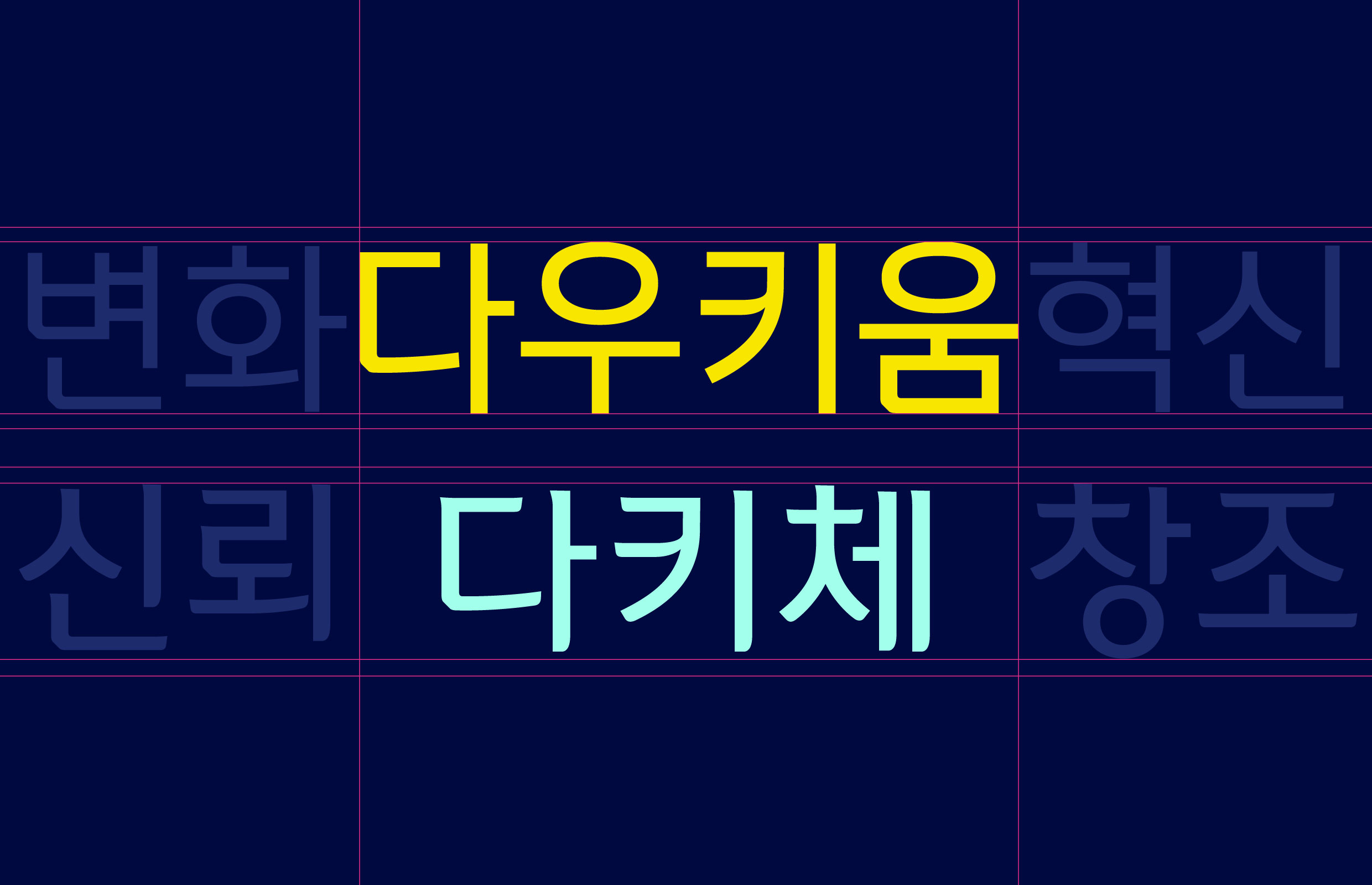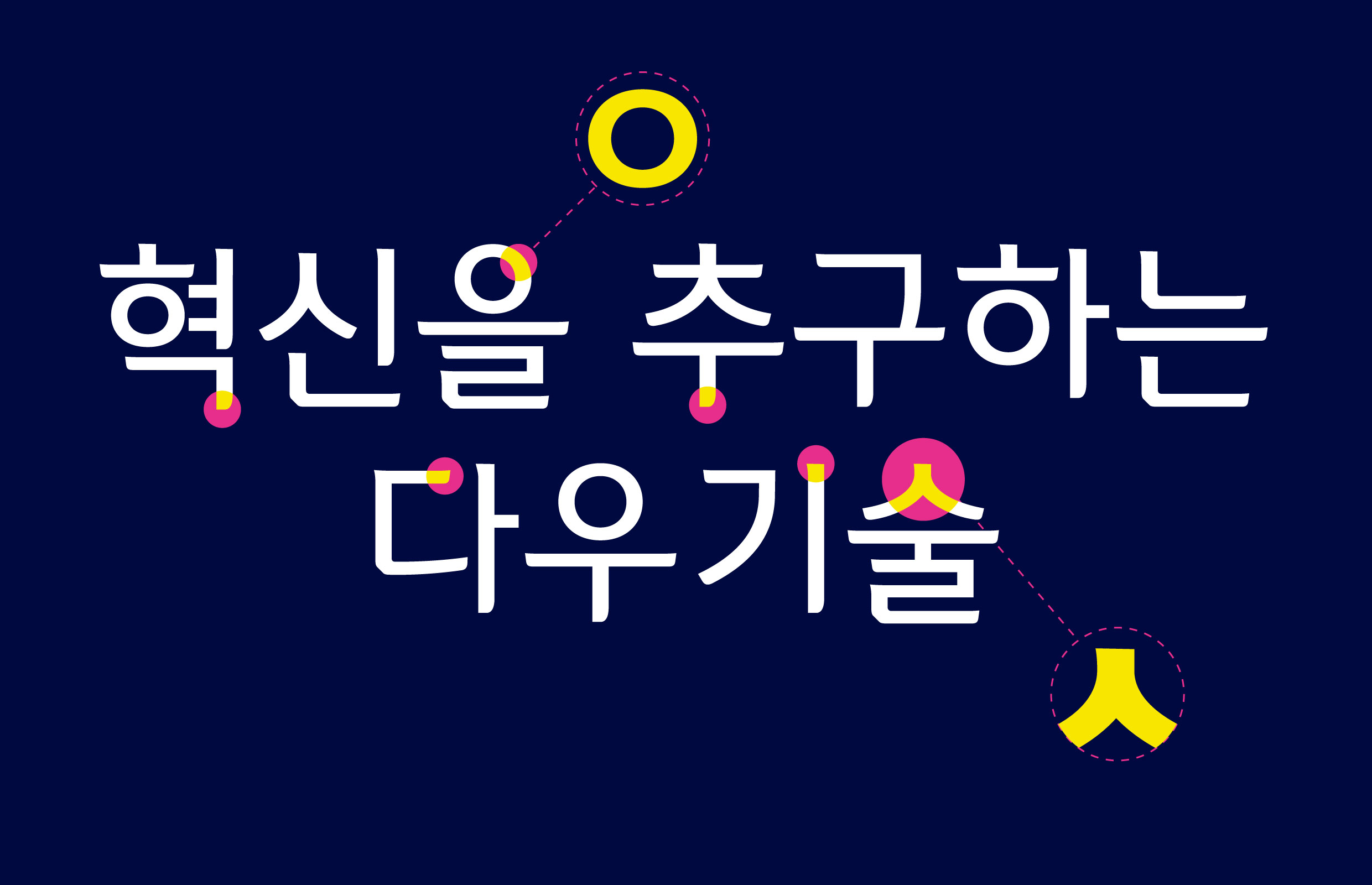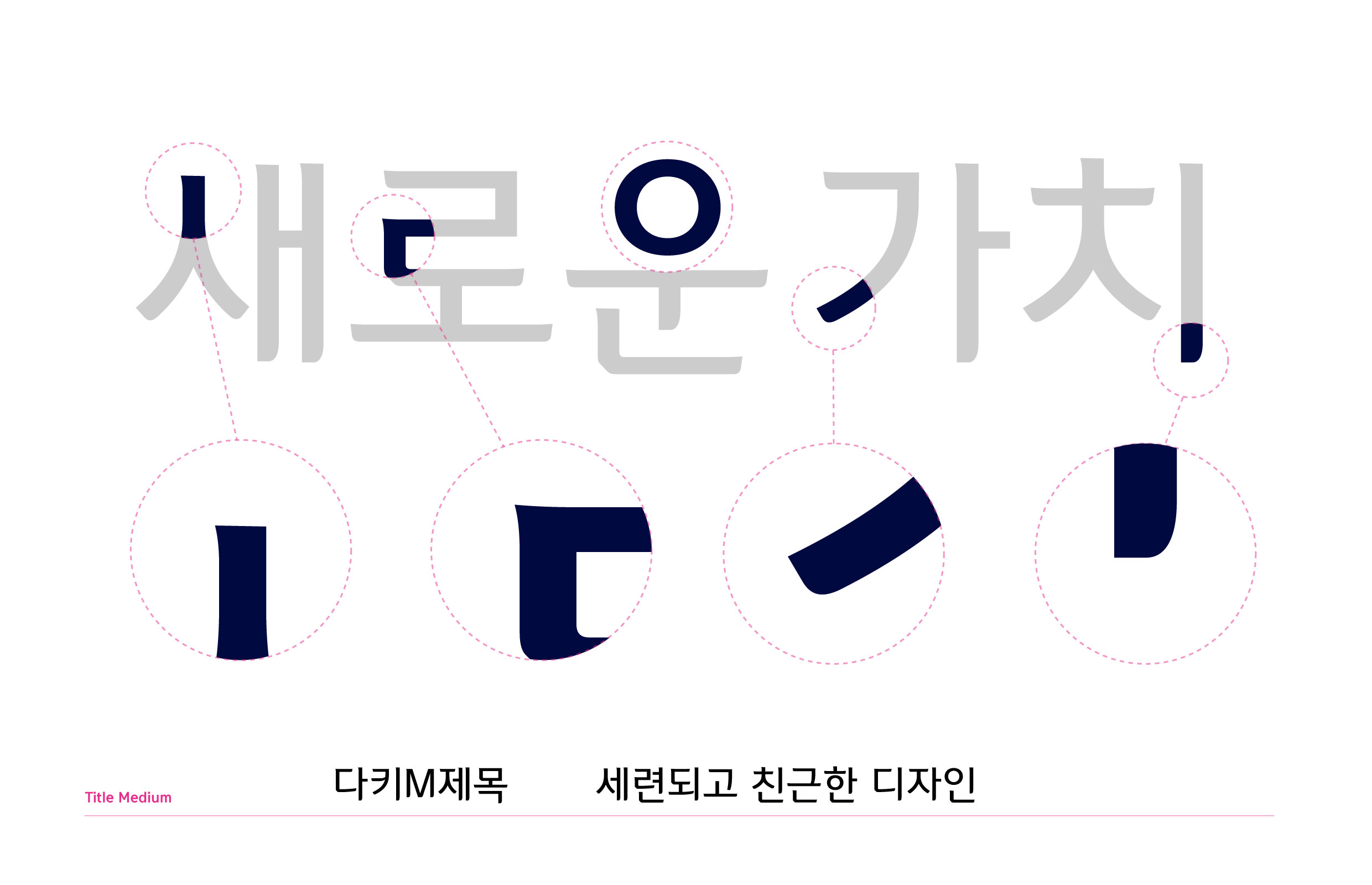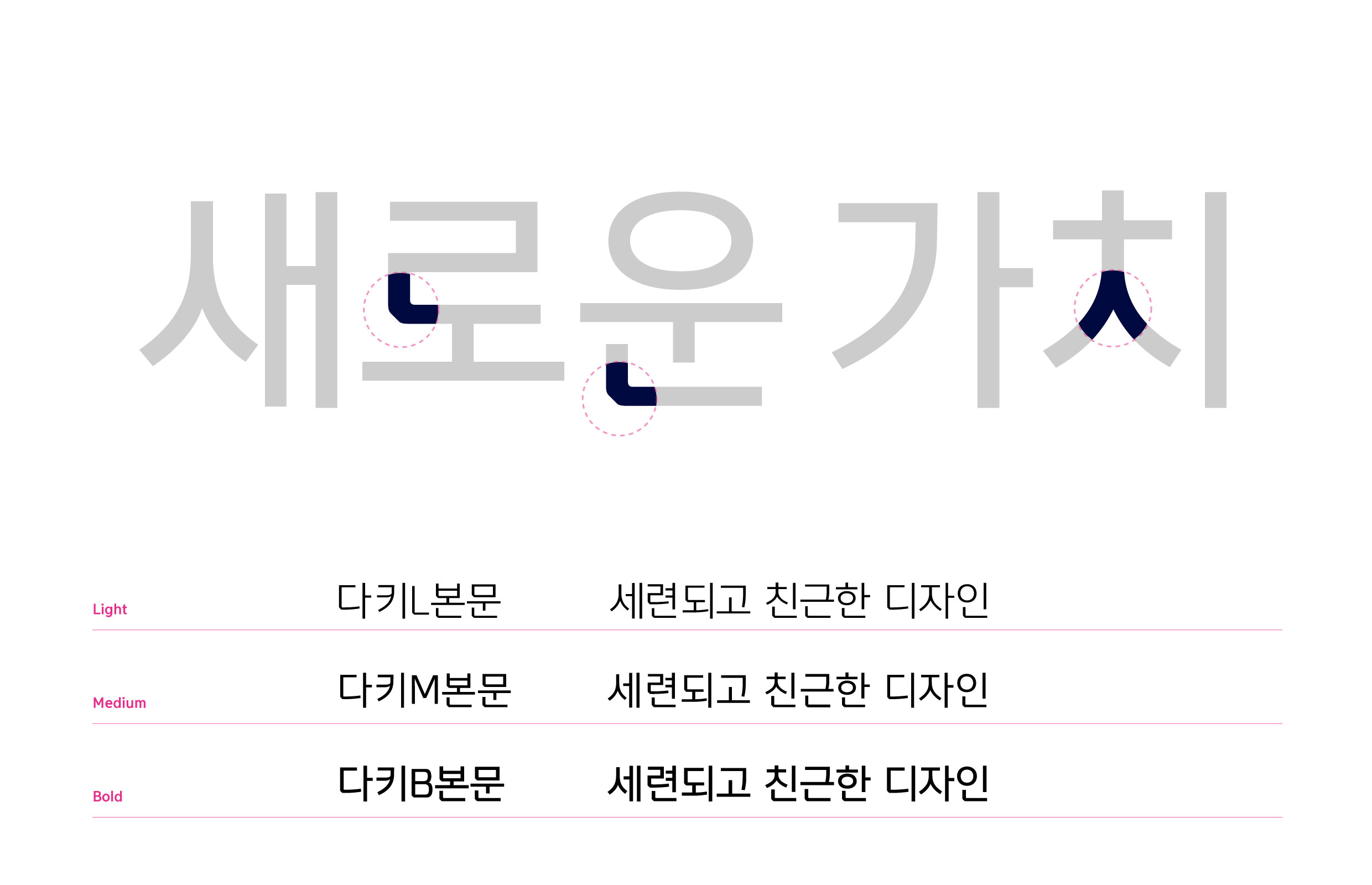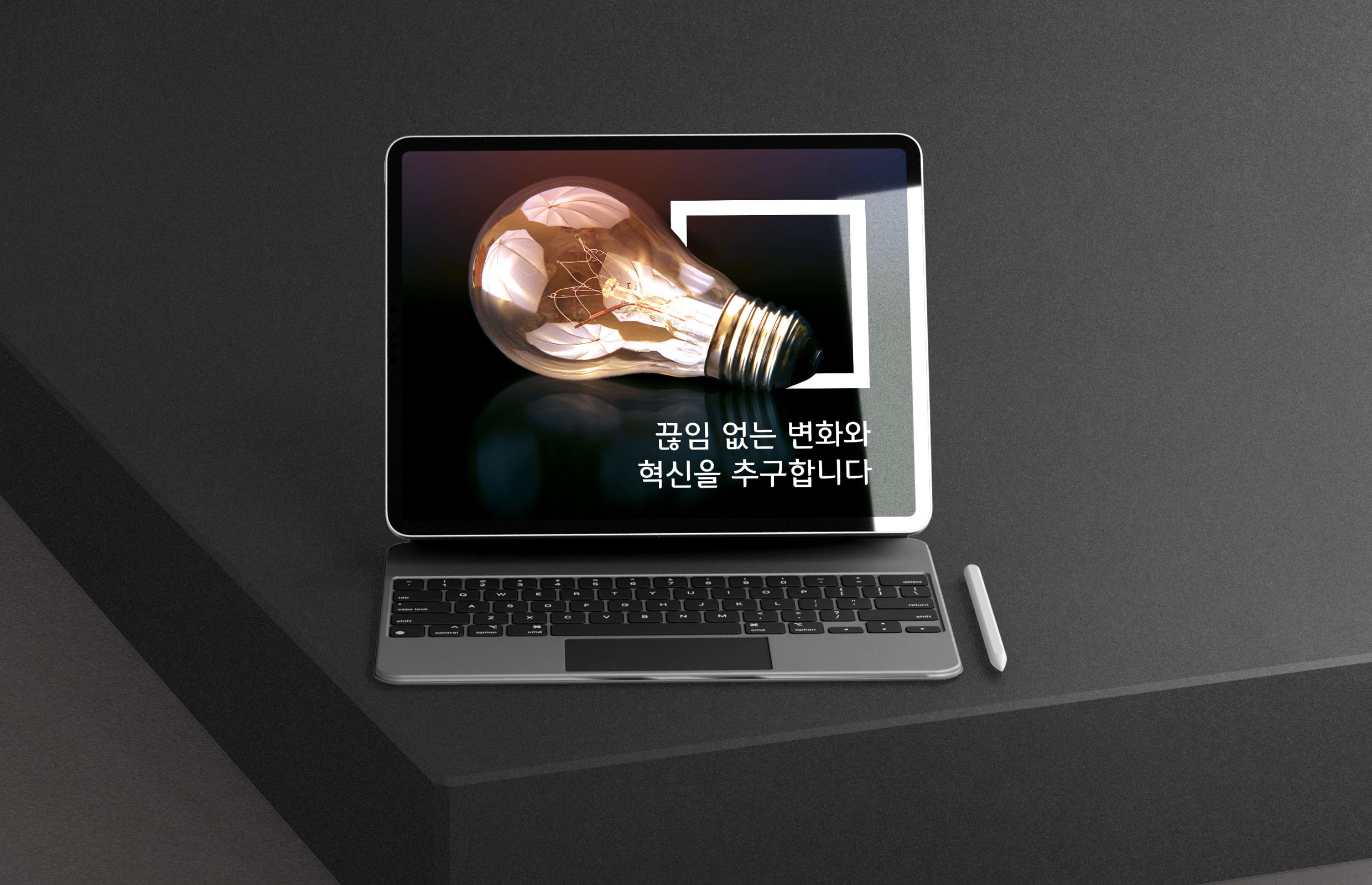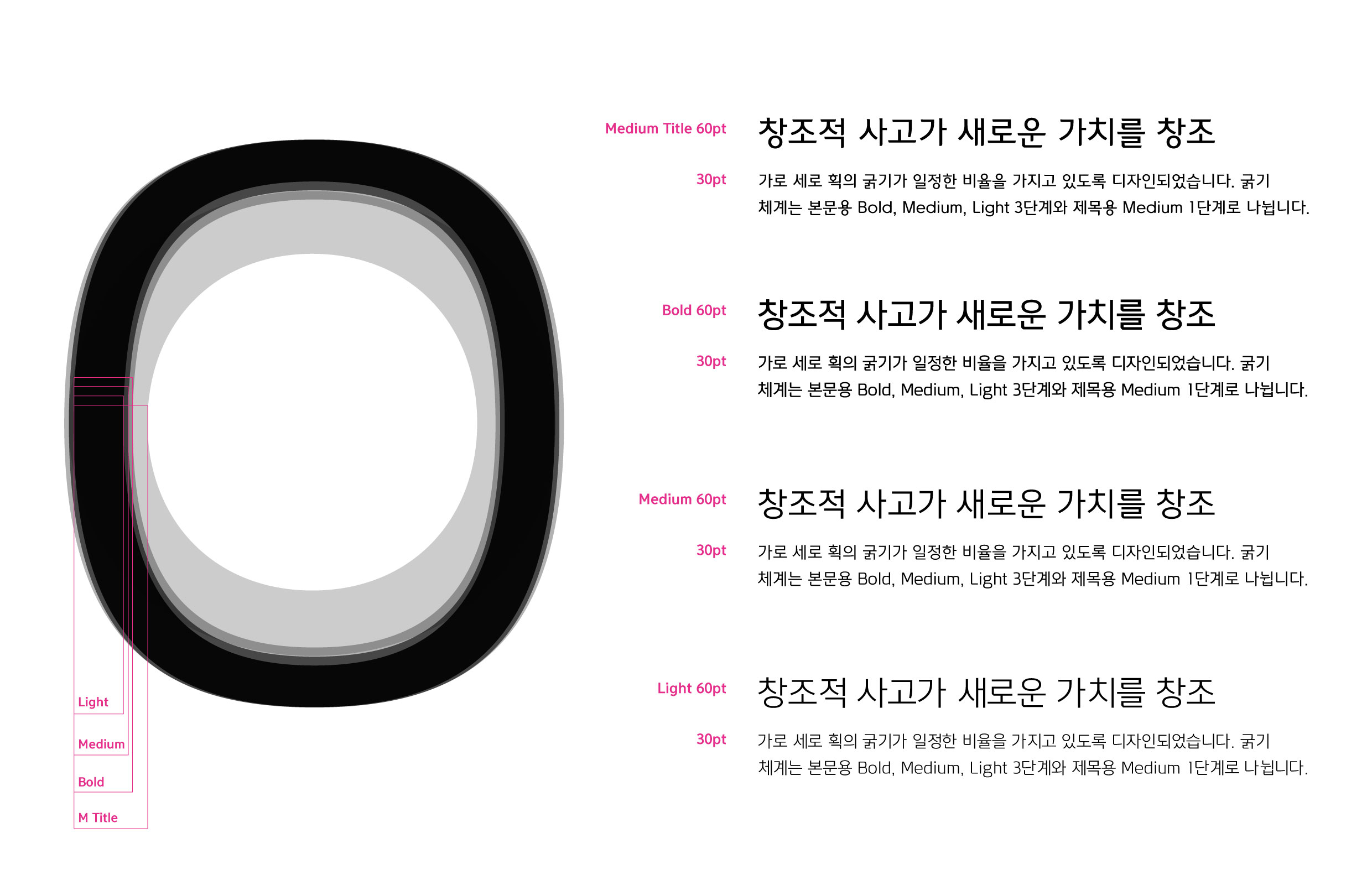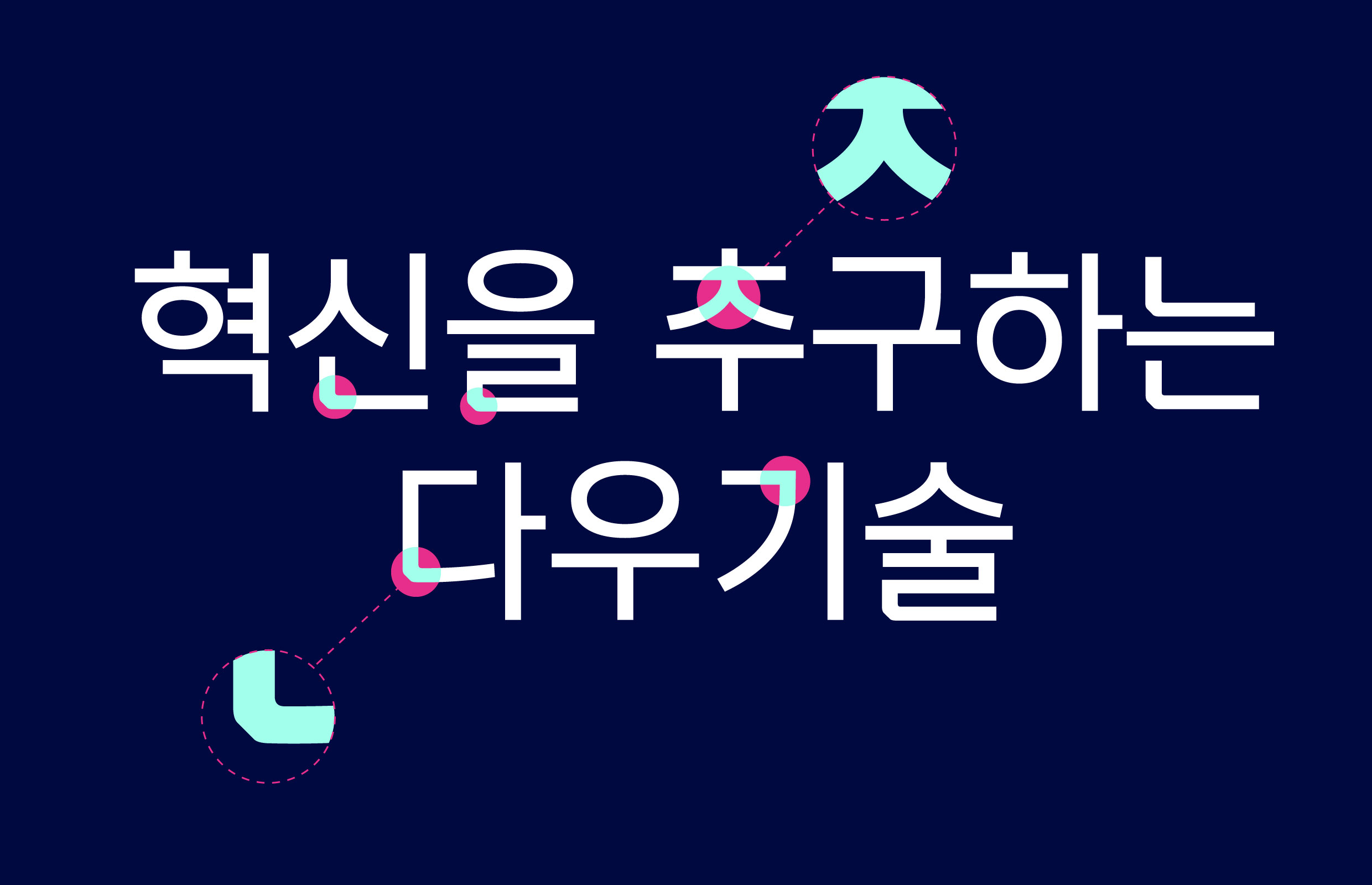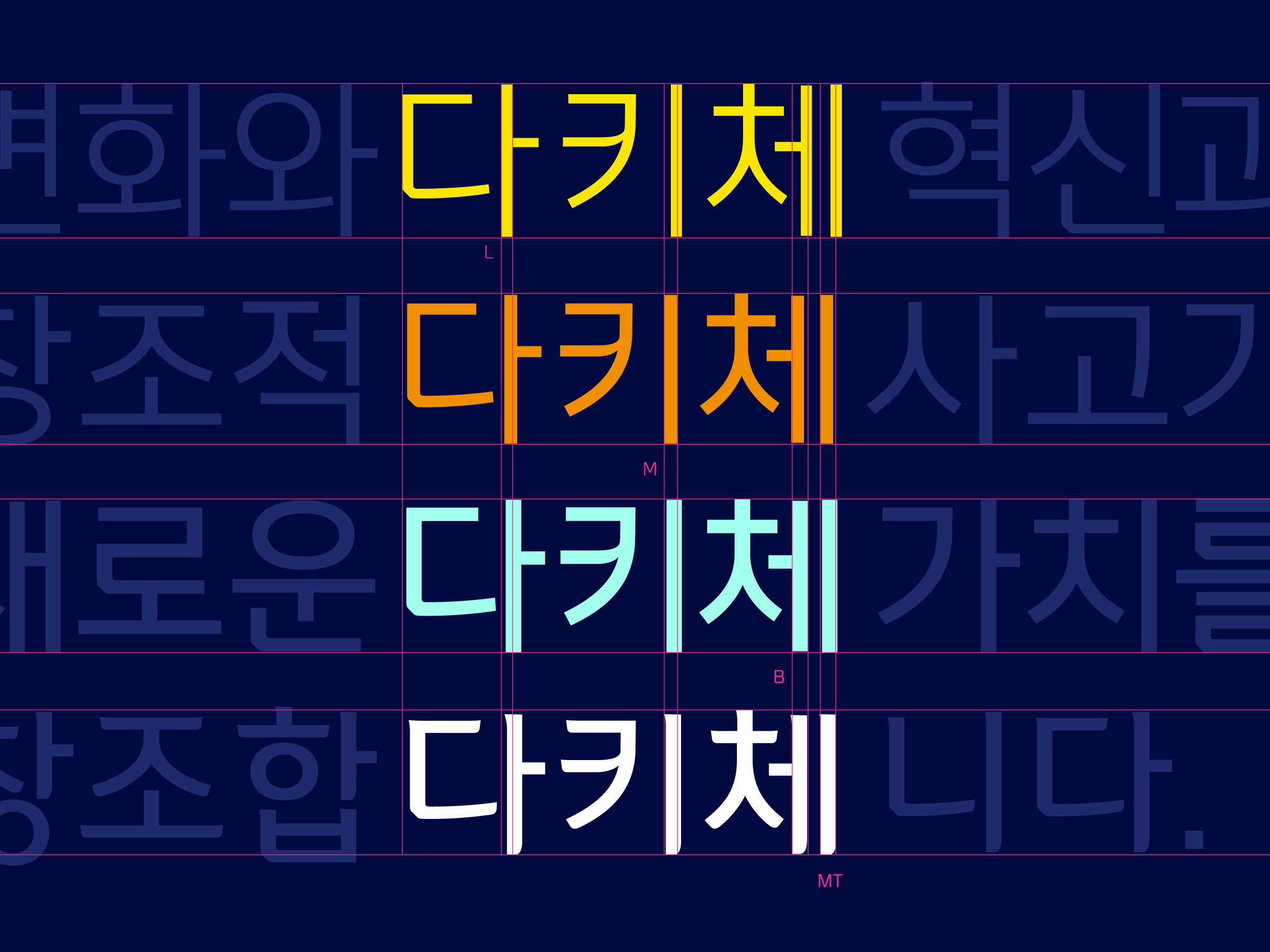
다우키움그룹 [다우키움]
다우키움그룹 시각 문화의 기초를 대변하는 서체. 안정적인 직선과 유기적인 곡선을 활용한 세련되고 친근한 디자인이 특징이며, IT 및 온라인 중심의 금융, 콘텐츠, 서비스 등 다양한 사업 분야를 지닌 다우키움그룹의 다채로움과 포용력을 내포하고 있다.